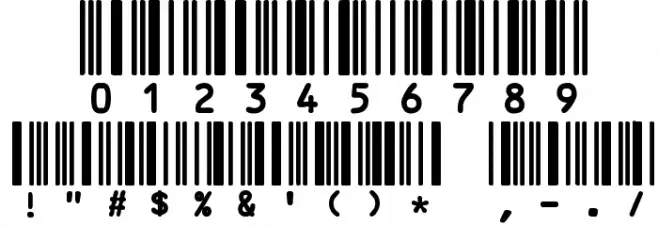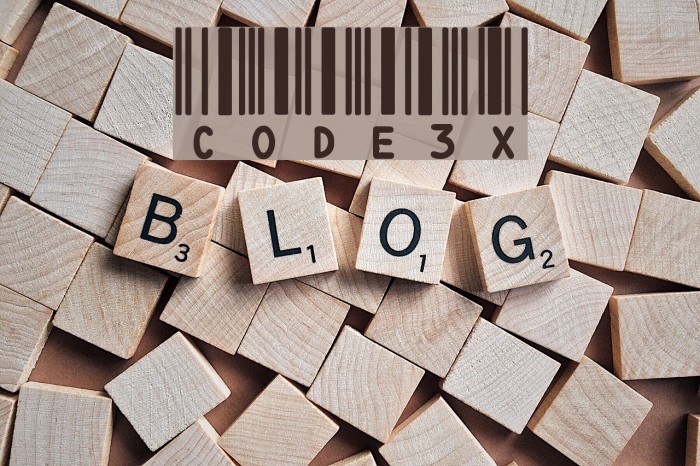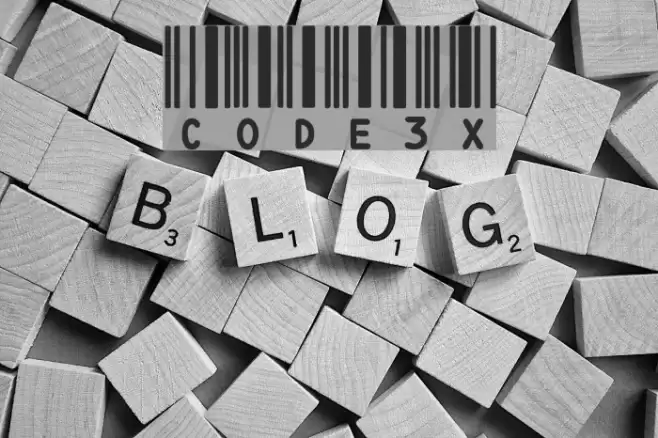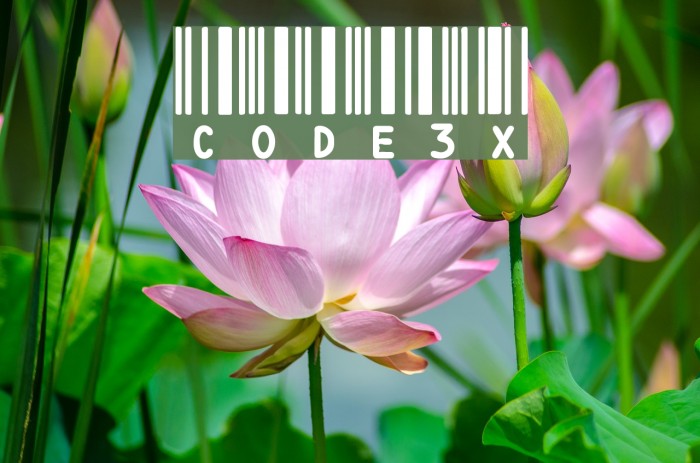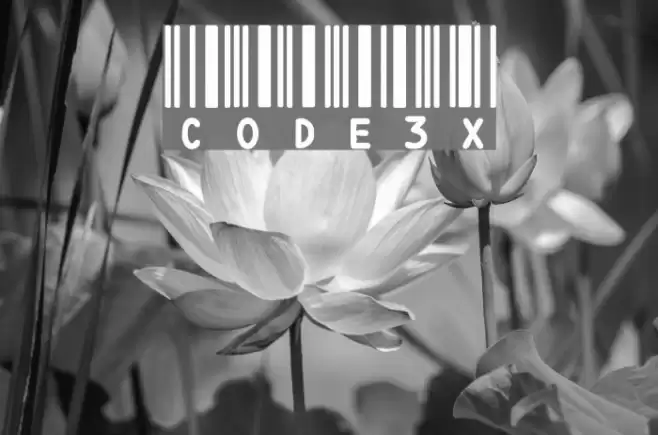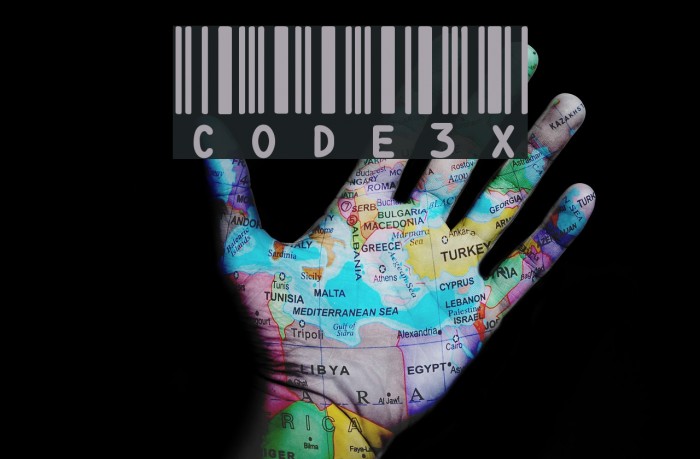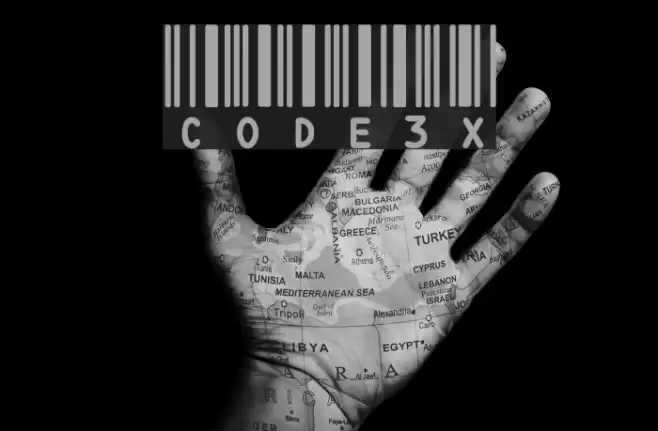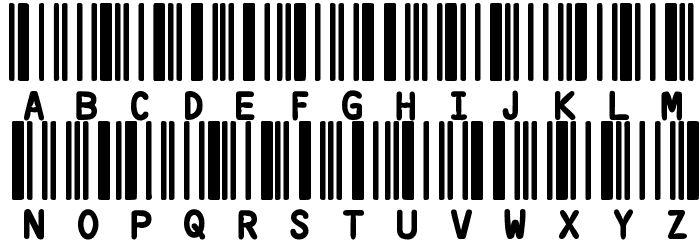
CODE3X Font
| Cas d'utilisation | Logos, Decorative elements, Themed designs |
| Projets proposés | Ideal for projects requiring a barcode aesthetic, such as themed posters, digital art, or creative packaging designs. |